Как использовать цветные шрифты для эмодзи и заголовков
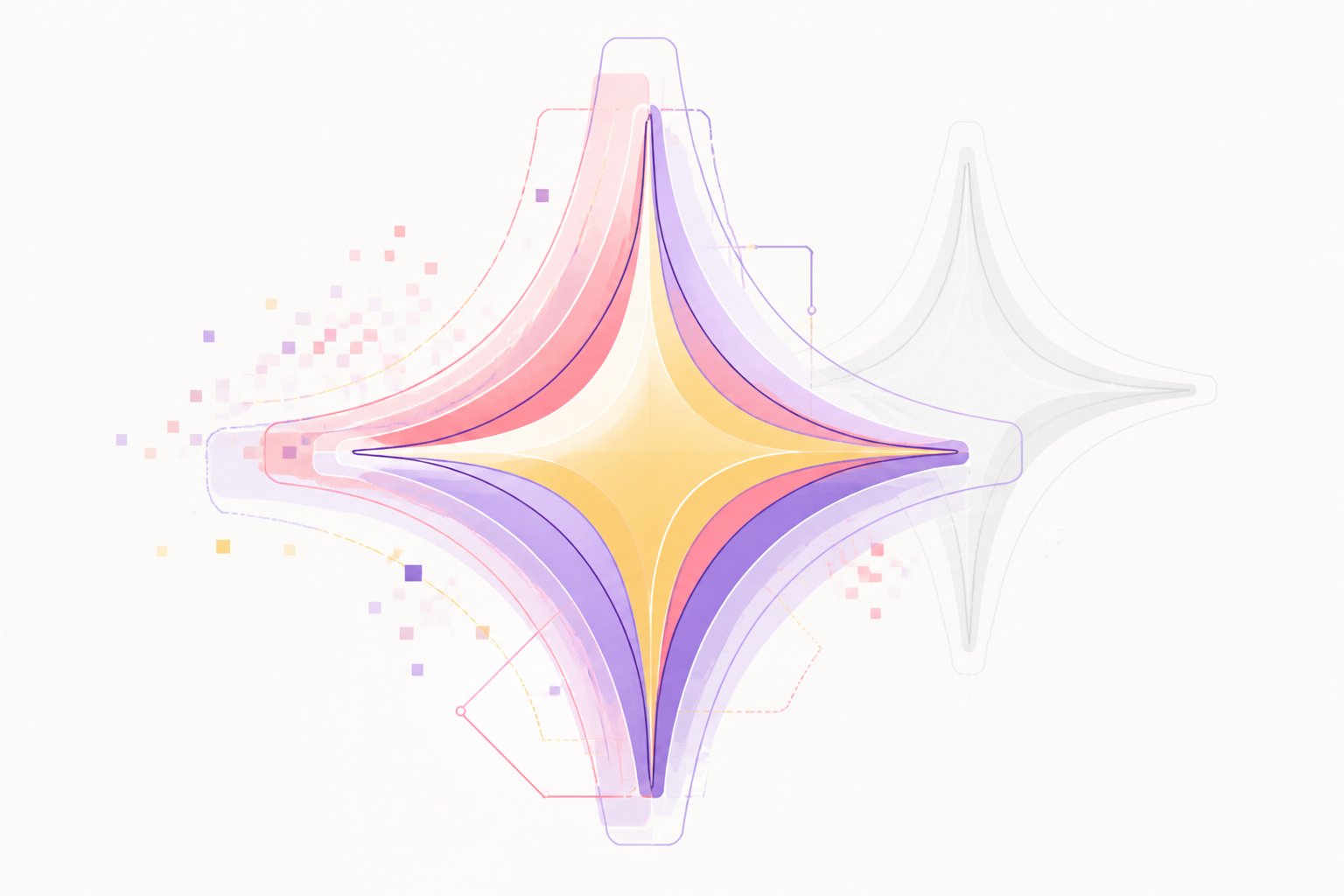
Что такое цветные шрифты
Цветные шрифты — это шрифтовые файлы, в которых отдельные символы могут содержать несколько цветов, слоёв, контуров, градиентов или растровых изображений. Их используют для эмодзи, логотипов, постеров, упаковки, игровых интерфейсов и декоративных заголовков. В отличие от обычного шрифта, цветной глиф задаёт не только форму буквы, но и её визуальное оформление. Поэтому одна и та же надпись может выглядеть как иллюстрация, пиктограмма или небольшая композиция.
Важно отличать цветной шрифт от текста, окрашенного средствами редактора. В обычном шрифте цвет задаётся всему символу целиком, а в цветном шрифте разные части одного глифа уже имеют собственные параметры. Например, буква может включать заливку, обводку, тень и отдельную декоративную деталь. Такой подход помогает сохранять сложную форму в виде текста, но требует проверки поддержки формата в конкретном приложении.
Какие технологии лежат в основе цветных шрифтов
В экосистеме OpenType применяются разные способы хранения цветных глифов. Форматы COLR и CPAL описывают векторные слои и палитры, поэтому подходят для масштабируемых эмодзи и декоративной типографики. OpenType-SVG использует SVG-описания и может хранить более сложные цветовые решения. Форматы CBDT и CBLC, а также sbix основаны на растровых изображениях и позволяют воспроизводить детализированные иллюстрации, но сильнее зависят от размера исходной графики и поддержки платформы.
Когда цветной шрифт уместен для эмодзи
Цветные шрифты особенно полезны, когда эмодзи должны быть частью композиции, а не отдельной картинкой. Их можно применять в заголовках рассылок, карточках социальных сетей, игровых меню, праздничных баннерах и интерфейсах с короткими подписями. Символ остаётся текстовым объектом: его проще заменить, выровнять и включить в строку. Это удобно для вариативных сообщений, где значок меняется вместе с текстом.
Практический пример — заголовок карточки «Новая коллекция ✨». Если звёздочка встроена в цветной шрифт, она может иметь собственные слои, обводку и характерную палитру. Однако эмодзи не должны конкурировать с главным сообщением. Для короткой фразы достаточно одного яркого символа, а для нейтрального делового текста лучше выбрать спокойную монохромную пиктограмму или обычный текстовый знак.
Как создавать декоративные заголовки с цветными глифами
Декоративный заголовок строится по тем же принципам, что и обычная типографическая композиция: сначала определяют смысл, затем иерархию, длину строки и контраст. Цветной шрифт стоит использовать как выразительный акцент, а не как замену всей системе оформления. Если каждая буква имеет сложную фактуру, строка быстро теряет ритм. Для длинных заголовков лучше ограничить декоративность отдельными символами, первой буквой или коротким словом.
Например, для афиши мастер-класса можно оформить слово «СТАРТ» шрифтом с двумя контрастными слоями, а пояснение «Практика для начинающих дизайнеров» набрать нейтральным гротеском. Такая пара сохраняет читаемость и создаёт визуальный центр. В веб-дизайне полезно заранее проверить переносы: декоративный глиф может иметь нестандартные боковые поля, из-за которых заголовок выглядит слишком разреженным или смещённым.
Пошаговый процесс работы с цветным шрифтом
- Определите задачу: эмодзи, короткий заголовок, логотипный акцент или набор пиктограмм. От цели зависит формат, размер и степень детализации.
- Выберите конструкцию глифа: слои, палитру, контур, растровую вставку или комбинацию этих элементов. Сначала решите, что должно оставаться узнаваемым при уменьшении.
- Подготовьте символы в векторном редакторе или шрифтовом редакторе. Проверьте замкнутые контуры, порядок слоёв, цветовые значения и отсутствие лишних узлов.
- Соберите тестовую версию шрифта и проверьте латиницу, кириллицу, цифры, знаки препинания и специальные символы, которые нужны конкретному проекту.
- Протестируйте шрифт в браузере, текстовом редакторе и графической программе. Сравните крупный размер, обычный заголовок и мобильный экран.
- Подготовьте резервный вариант: обычный шрифт, SVG или изображение. Это позволит сохранить композицию, если цветные глифы не поддерживаются.
- Опубликуйте результат после проверки лицензии, читаемости и веса файлов. Для сайта подключайте только нужные начертания и символы, если такой способ оптимизации доступен.
Как подобрать палитру и контраст
Палитра цветного шрифта должна поддерживать смысл и фон, а не просто демонстрировать максимальную насыщенность. Для эмодзи обычно работают локальные контрастные цвета, которые быстро считываются в маленьком размере. Для декоративного заголовка полезнее ограниченная палитра из основного цвета, акцента и нейтрального оттенка. Если каждый слой использует новый цвет, буквы начинают восприниматься как случайный набор деталей.
Проверяйте контраст не только в исходном макете, но и в реальном сценарии: на светлом и тёмном фоне, при уменьшении, в режиме пониженной яркости экрана и рядом с обычным текстом. Не полагайтесь исключительно на цвет для передачи важного смысла. Статус, ошибка или предупреждение должны дополнительно обозначаться словом, формой или расположением, особенно в интерфейсе.